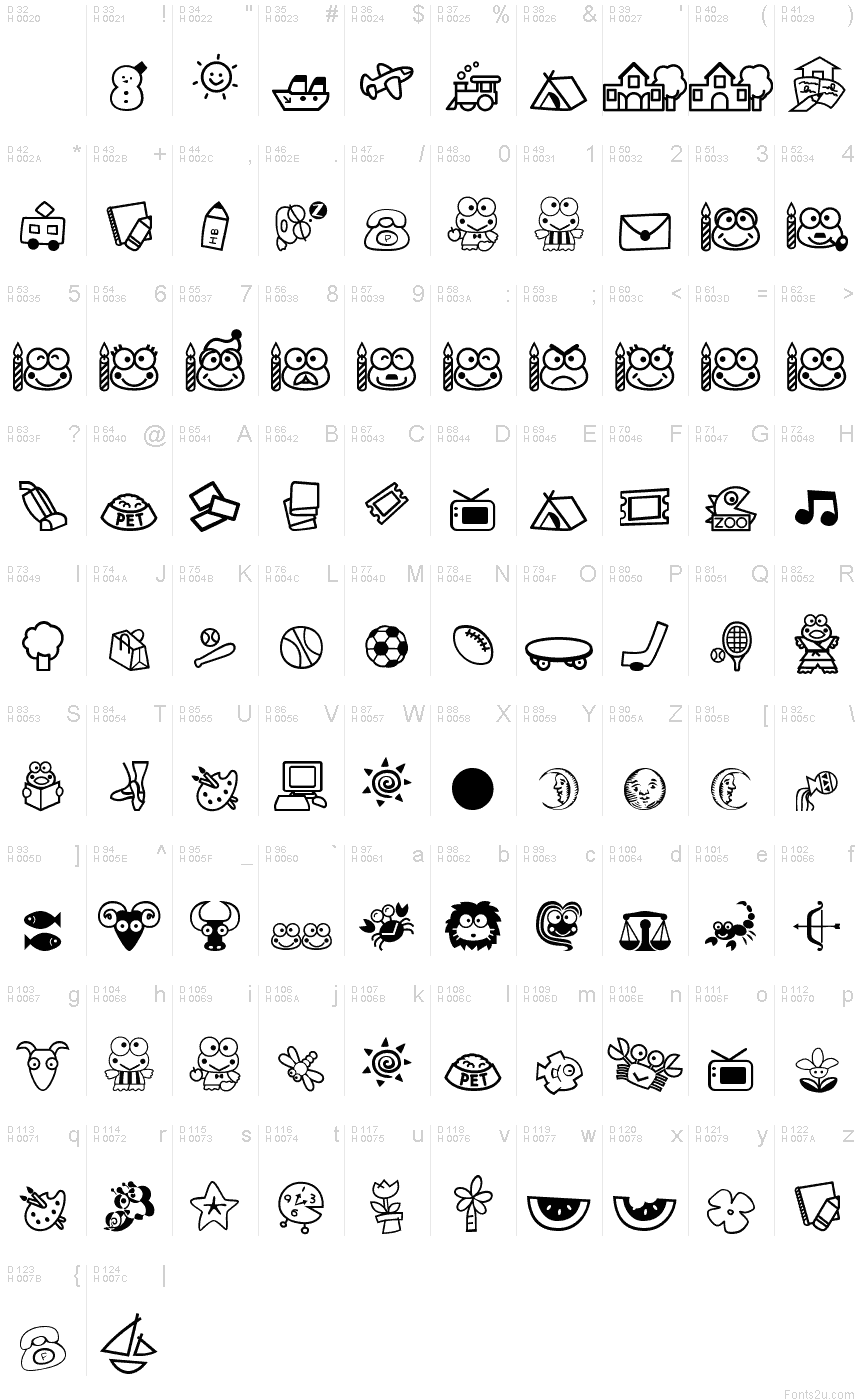
Keroppi to darmowy krój typu dingbat, który zmienia Twoją klawiaturę w zestaw pełen zabawnych ikon. Od uśmiechniętych krabów i ślimaków z zawijasami, po kanciaste telewizory i kwiatki jak z kreskówki – każdy znak jest wyrazisty, „atramentowy” i niezwykle przyjazny. Sylwetki są czyste i kontrastowe, dzięki czemu pozostają czytelne nawet po zmniejszeniu, a przy większych rozmiarach wyglądają zabawnie i energicznie.
Dzięki Keroppi możesz szybko dekorować szkolne karty pracy, plakaty, zaproszenia urodzinowe, naklejki, książeczki z zadaniami i strony do scrapbookingu bez konieczności szukania clipartów. Ikony wstawia się jak pieczątki, co dodaje energii i charakteru każdemu projektowi. Ten darmowy font świetnie komponuje się z zaokrąglonym krojem bezszeryfowym o rozmiar lub dwa mniejszym, dzięki czemu dingbaty pozostają głównym elementem układu.